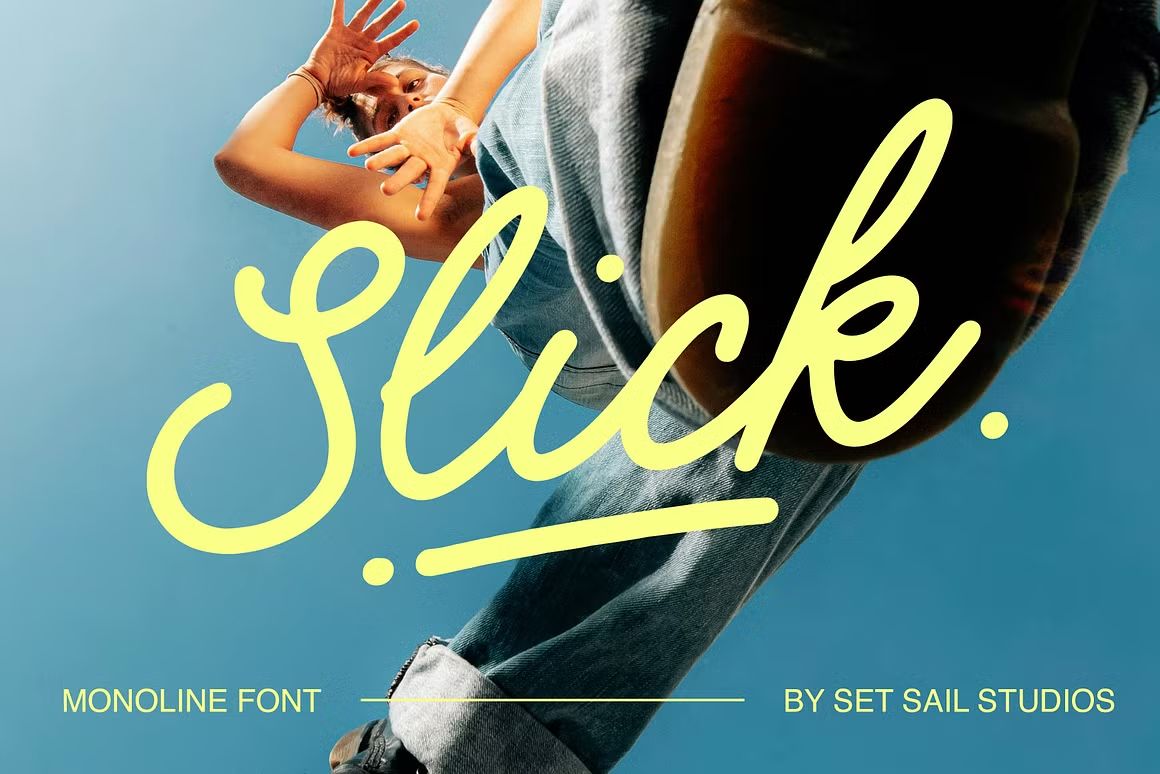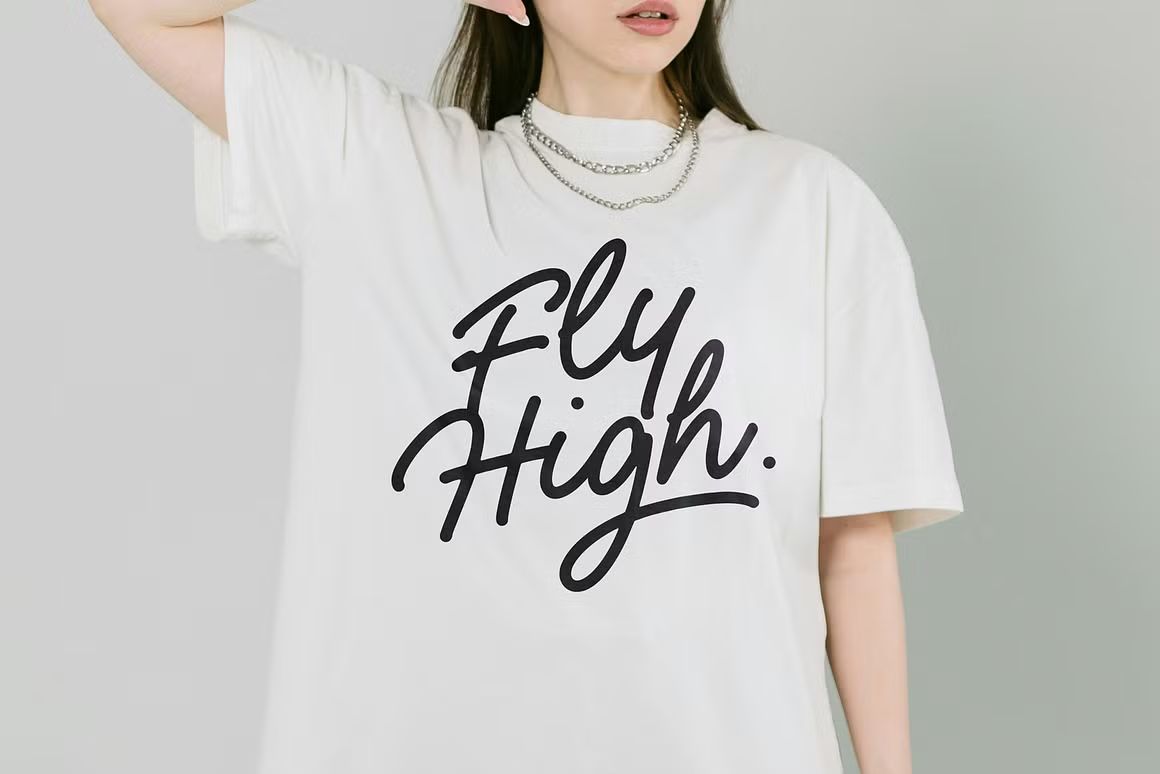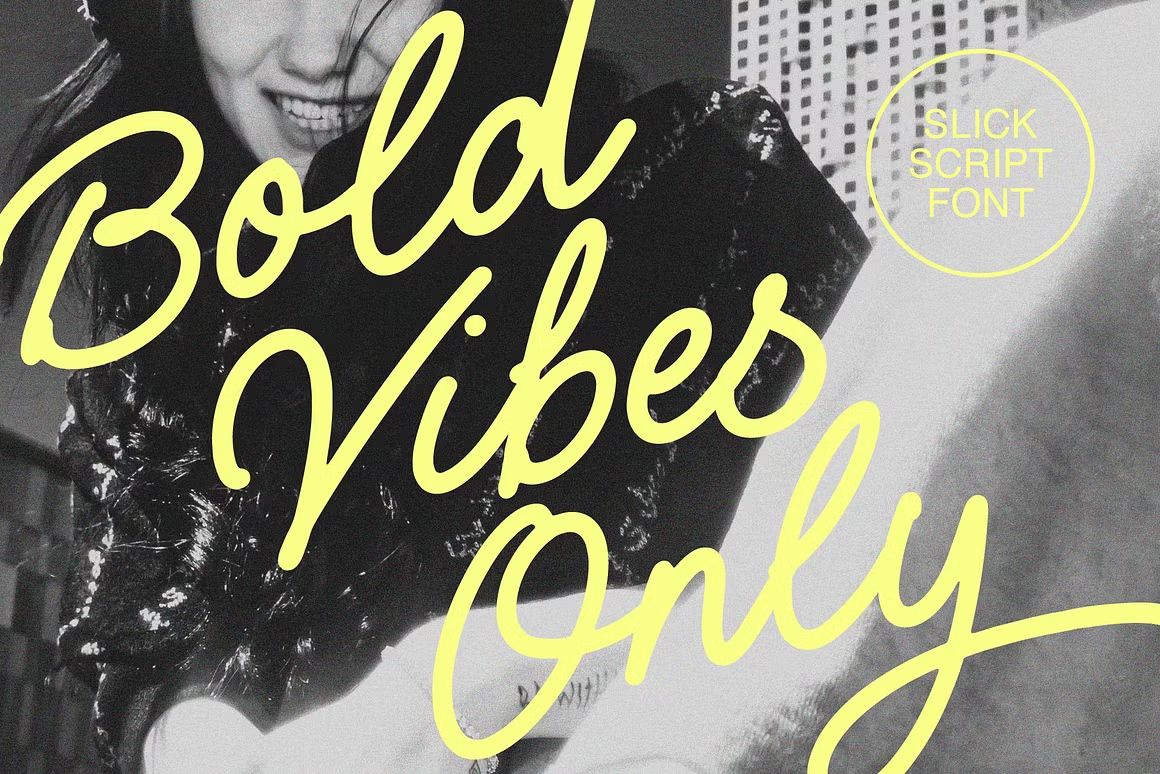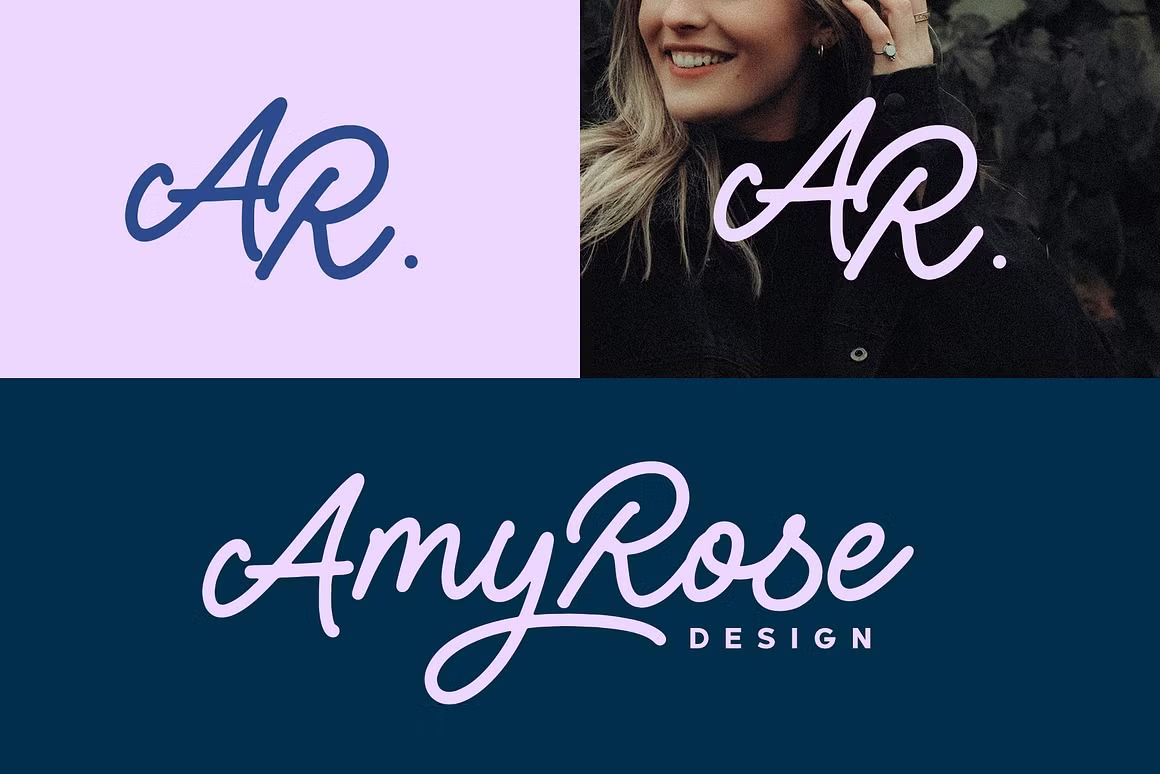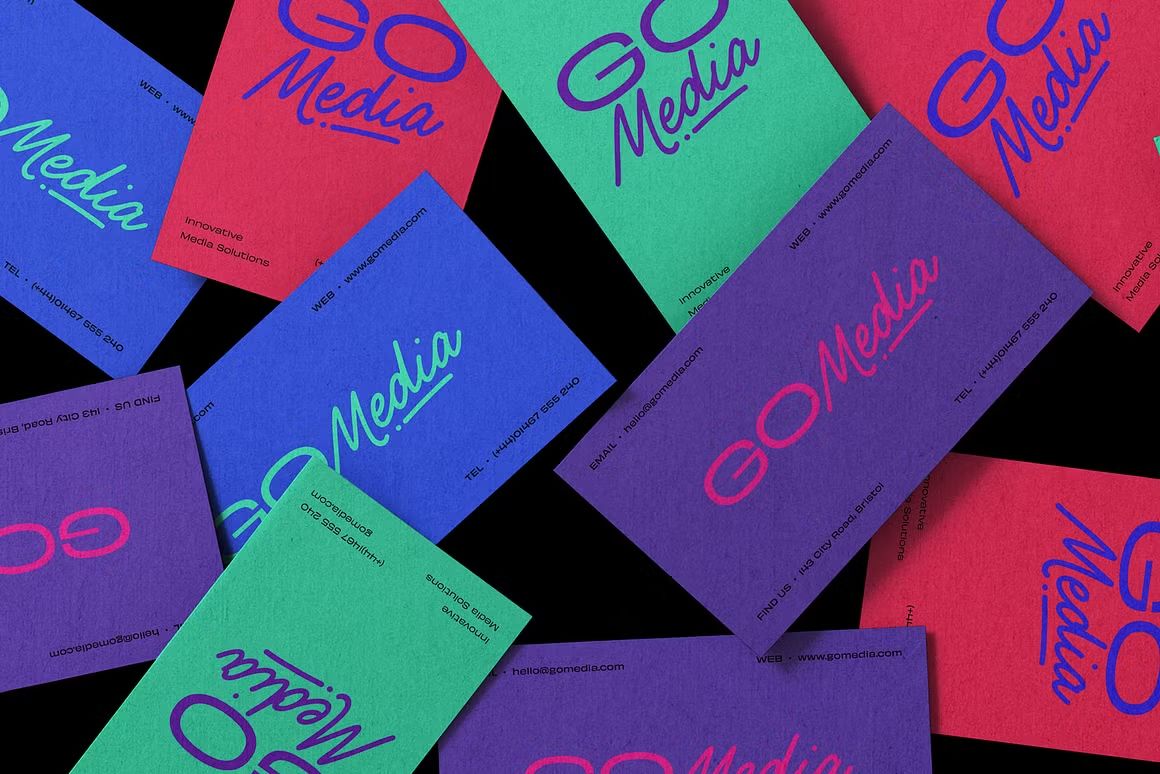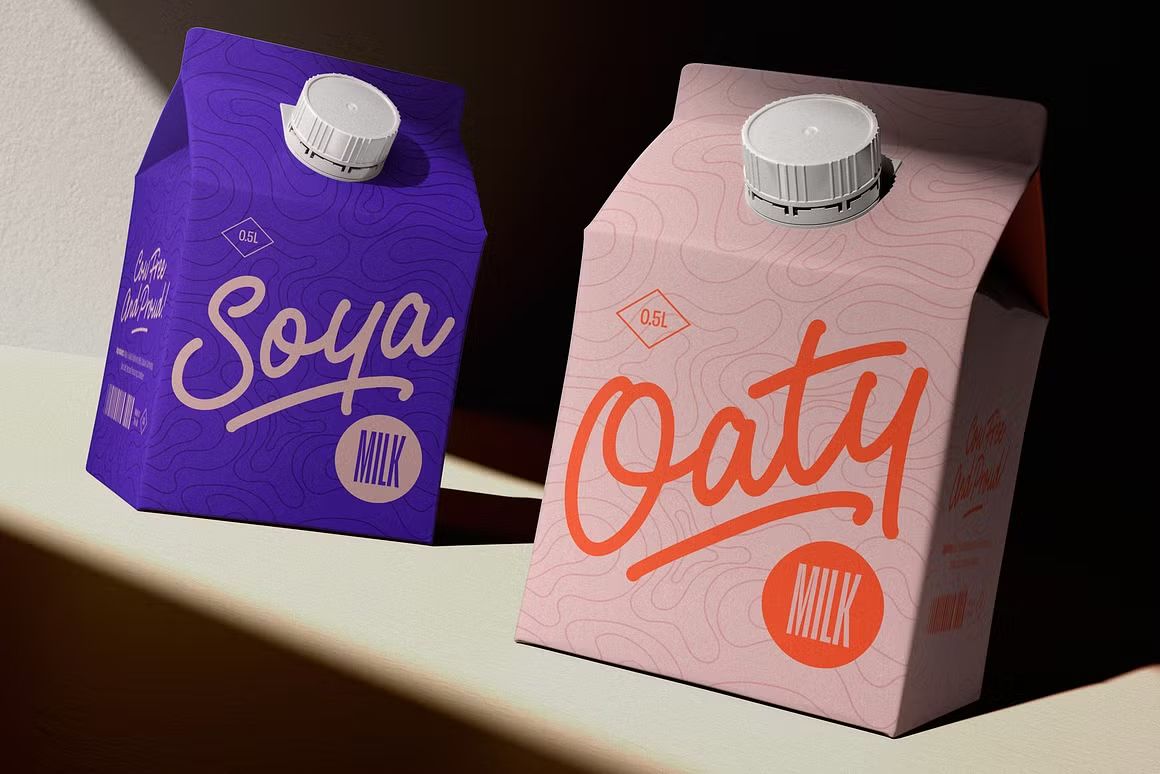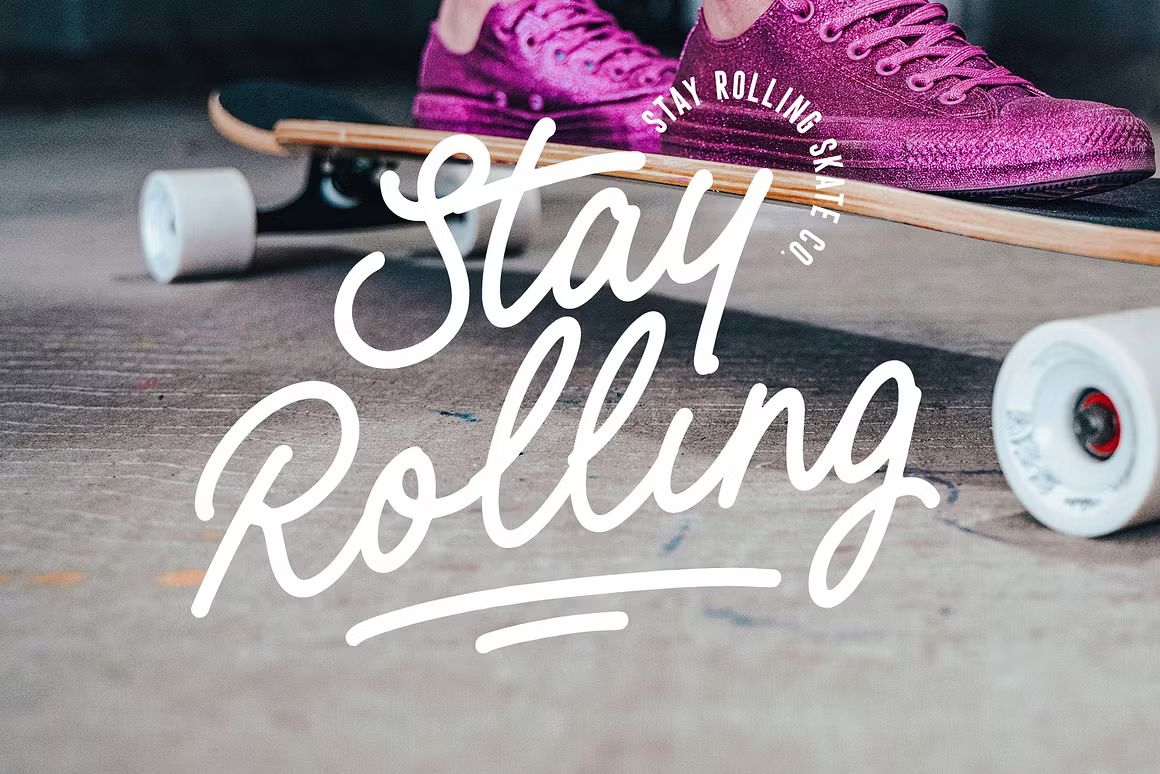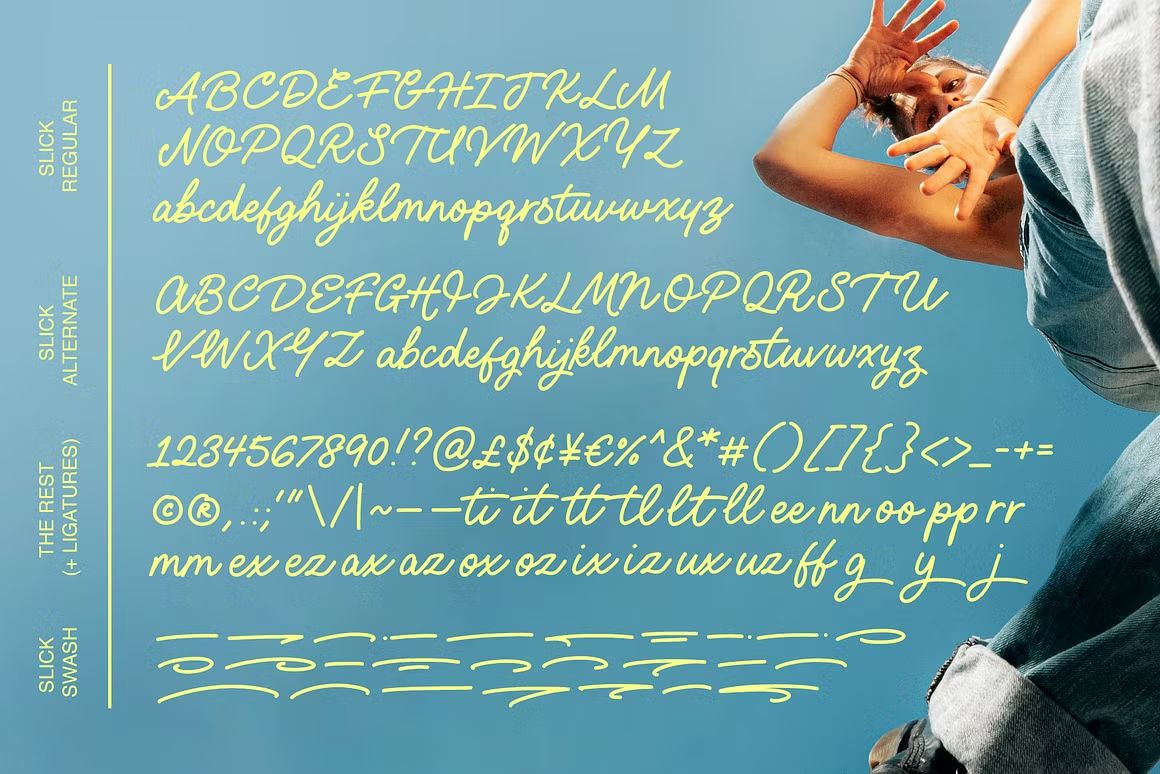
Slick – Script Font
Slick adalah font script modern dengan gaya tulisan tangan yang halus dan dinamis, sempurna untuk logo, branding, undangan, dan desain kreatif yang membutuhkan tampilan elegan dan stylish.
Slick adalah font script modern dengan garis halus dan lekukan dinamis, menciptakan tampilan elegan dan stylish. Dengan desain tulisan tangan yang bersih dan mudah dibaca, Slick sangat cocok untuk logo, branding, undangan, kartu ucapan, dan proyek desain lainnya yang membutuhkan kesan profesional namun tetap kreatif.
Fitur unggulan:
• Gaya script modern dengan garis halus dan dinamis
• Cocok untuk logo, branding, undangan, kartu ucapan, dan desain kreatif
• Termasuk huruf besar, huruf kecil, angka, dan simbol lengkap
• Ideal untuk proyek cetak dan digital yang membutuhkan tampilan elegan dan profesional